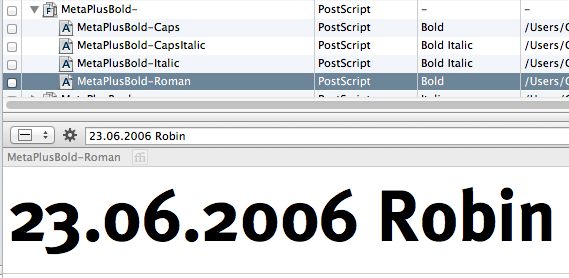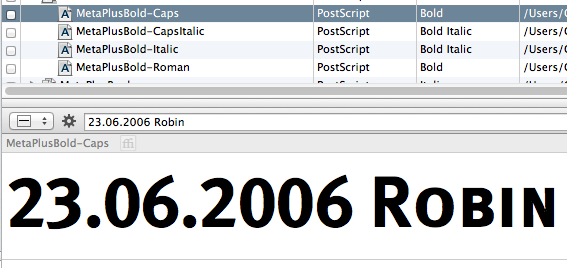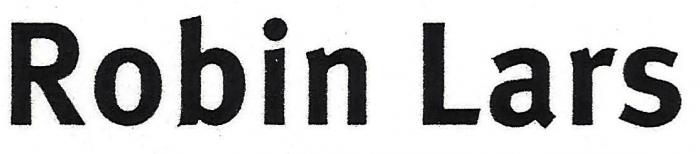
Welche Schrift ist das??
ich hoffe ihr könnt mir weiterhelfen. Von unserem alten Briefbogen habe ich ein teil der schrift als bild angehängt. vielleicht könnt ihr mir sagen welche schriftart das ist. die firma, die uns die briefbögen mal gemacht hat gibt es nicht mehr und wir haben von denen auch keine rohdaten erhalten. daher jetzt meine frage an euch.
danke. das war die richtige schrift. daaannnkkkkeee.
jetzt allerdings gleich das nächste problem. ich habe mal ein datum angehängt. scheint die selbe schriftart zu sein, allerdings sind die zahlen bei der meta bold gedrungen und versetzt, vorallem die 0. (bild 1) es müsste aber aussehen wie das angehängte datum (bild 2).
Das obere Beispiel sind die Mediävalziffern, das untere die Versalziffern. Kannst du beispielsweise bei den Opentype-Funktionen einstellen (bin mir aber nicht sicher, weil ich nur eine alte PostScript-Version hab). Oder du nimmst die Ziffern aus der MetaCaps, die hat default Versalziffern.
ich wußte gar nicht, dass es von einer schriftart soviele verschiedene typen geben kann.